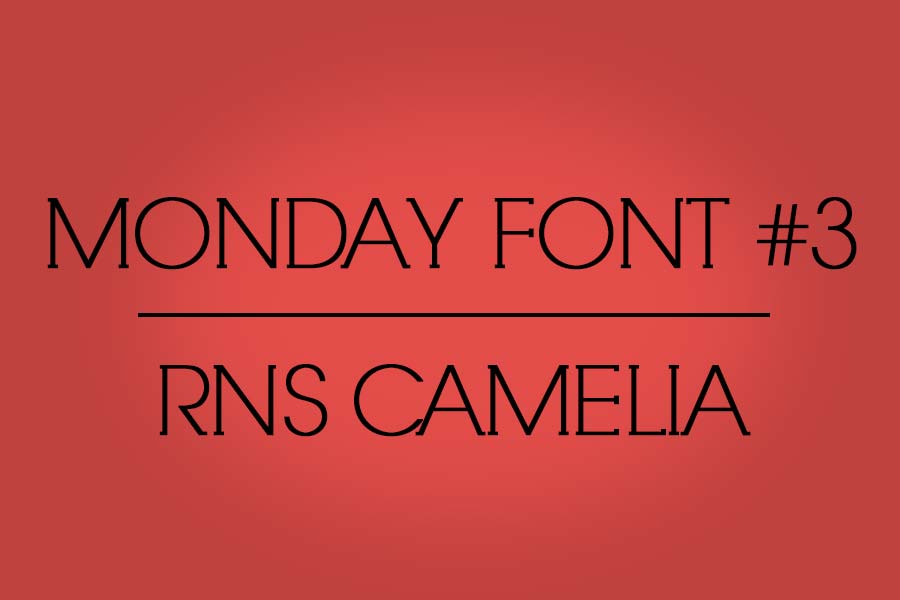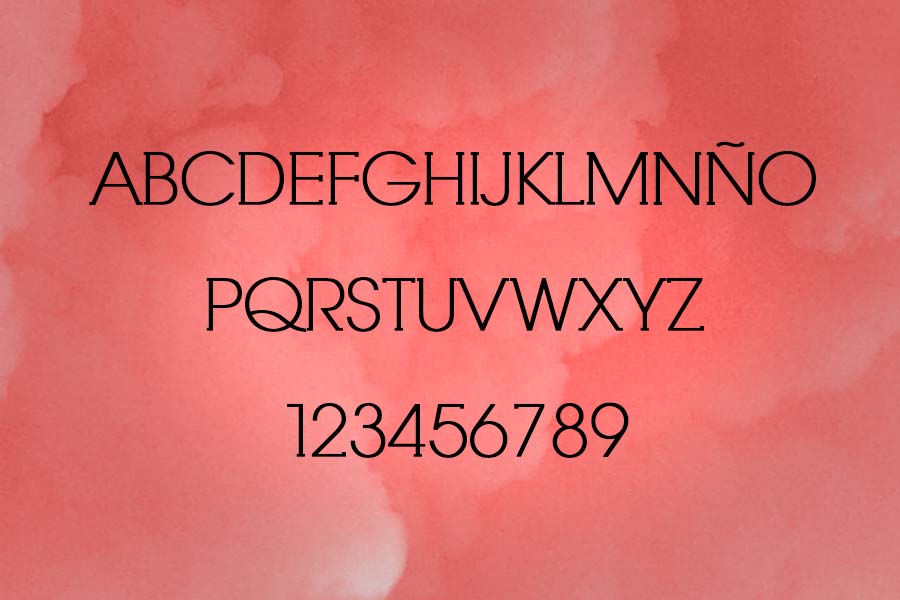
Un lunes más estamos devuelta con Monday Font, un especial donde recomendamos una fuente tipográfica para descarga totalmente gratuita.
Hoy os presentamos RNS Camelia una fuente fina y elegante con serifa que particularmente me encanta. Esperamos que a vosotros también ;)